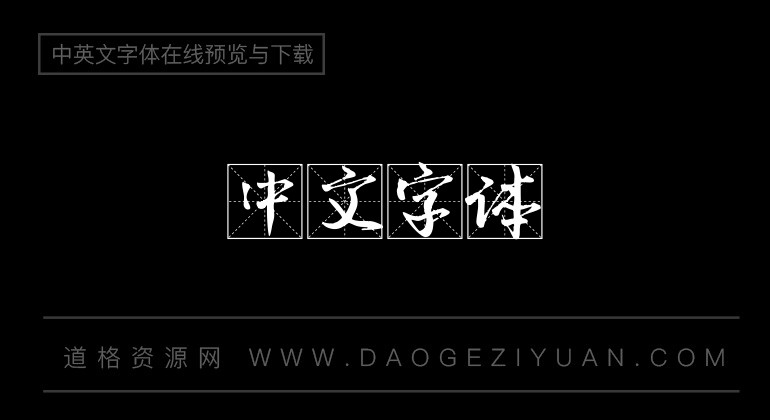
山魂田格是一款繁体中文字体,它的设计灵感来源于山的精神,以及古典文字的美感。字体的设计充满了古朴的气息,每一个字都有自己的独特性,让人感受到它的历史感。字体的细节处理得很好,使它具有良好的可读性和可视性,让人们更容易理解和阅读。它还具有强大的多语言支持,可以支持多种语言,让它在国际上更具有吸引力。文件名:ShanHunTianGeMoJi-2.ttf
山魂田格是一款非常不错的手写艺术字体,具有很好的视觉感,适合于文化类的宣传设计、商业类品牌的广告和产品包装设计以及个性化文字排版等较多场景。